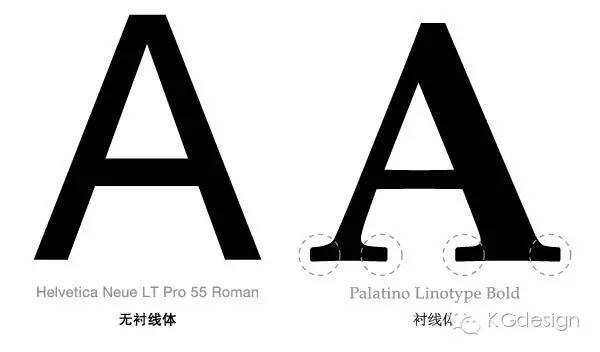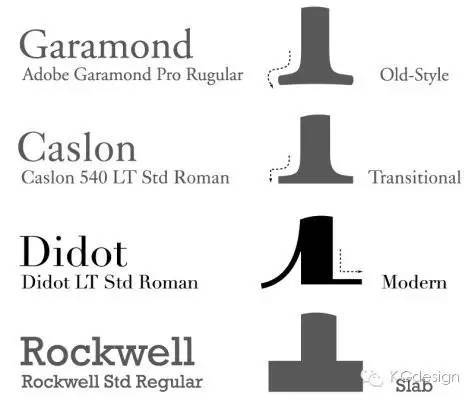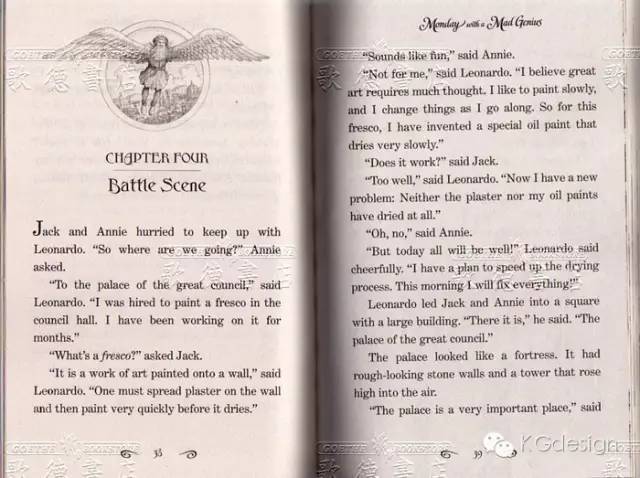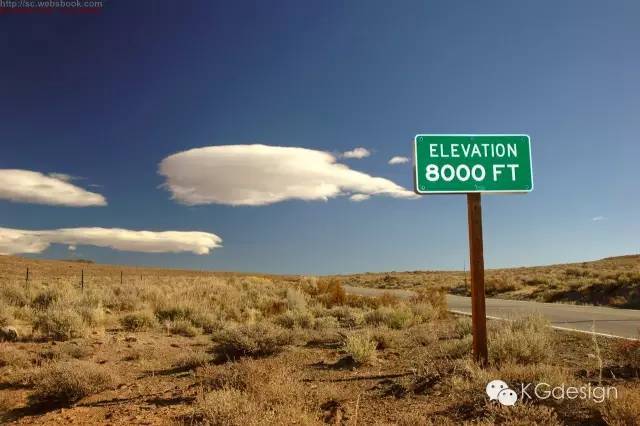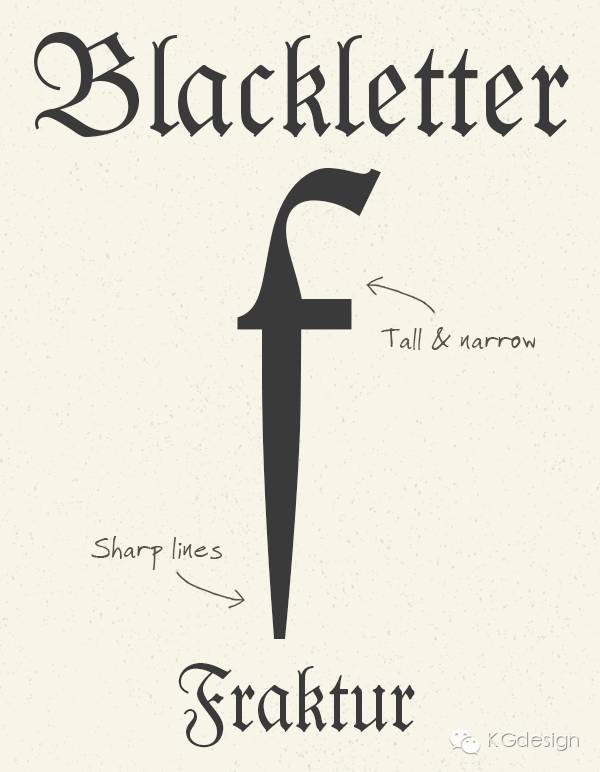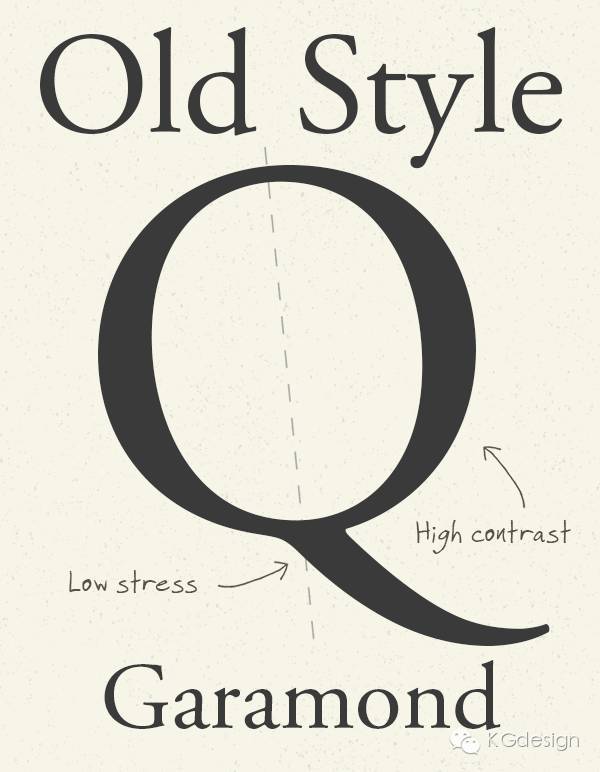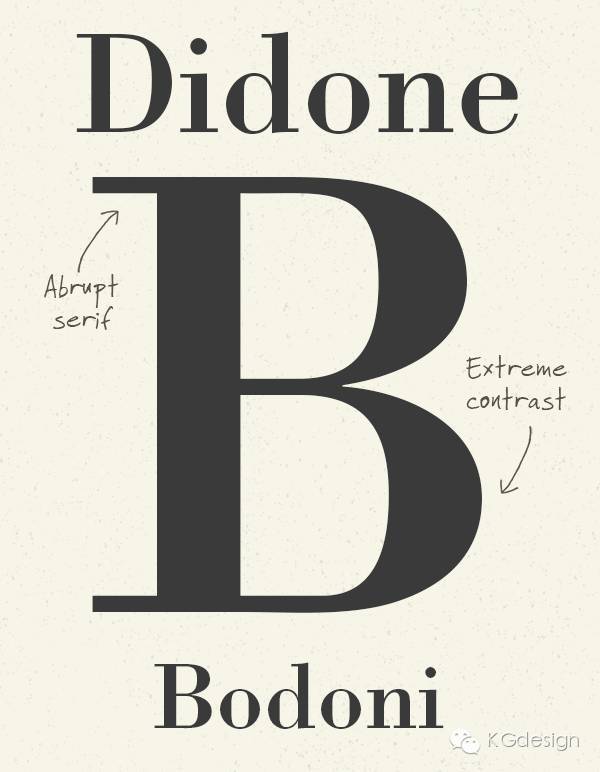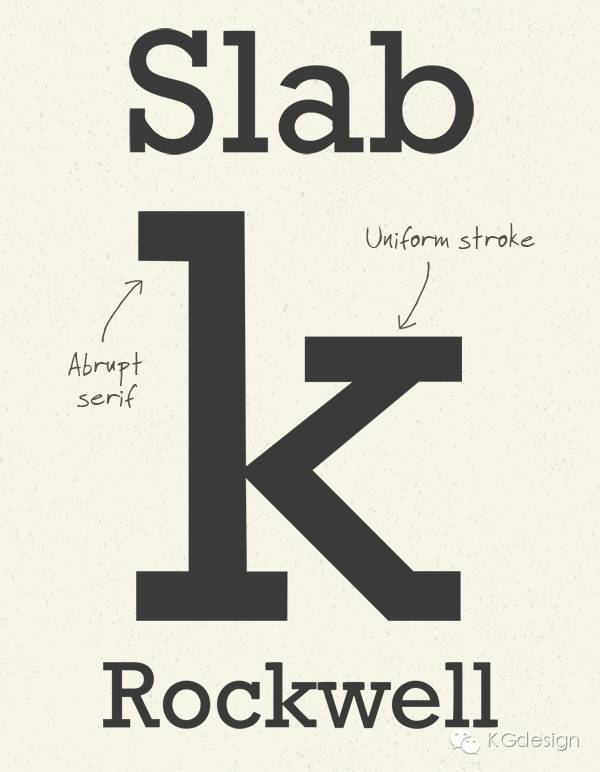
如何选择合适的字体?一文告诉你怎么办
在平面设计中,字体的重要性仅次于排版。不同于活字印刷的年代。以如今的网络环境而言,有成千上万种字体可以供设计师和各类从业者自由下载,那么当我要排一份ppt、论文、海报、画册时应该如何选择字体?这里试着简单的表达一些我对这个问题的理解。
将成千上万种字体进行归类和总结是个费神的工作,印刷工人和设计师们将字体粗分为衬线字体、无衬线字体、手写体三个类别。
手写体就不废话了,先来明确一下什么是所谓的衬线
如上图所标注的
衬线指的是字体笔画末端的装饰线条。
一般认为所谓的衬线最早是在操作雕版印刷时为了避免平行于木纹的线条破损,所以开发出的横向线条纤细而纵向线条粗壮的字体。
设计师总是倾向于在段落文字中使用衬线字体。因为衬线体被认为比无衬线体更易于阅读,是更正统而与正式的。
相对的各种标牌与指示系统则大量的使用无衬线字体,相信是出于易于辨别与制作成本的考虑。
衬线体
这种存在了几个世纪的字体在设计中主要用于表达专业、古老、正式、传承一类的情感。横竖线条的线宽差越大越会表达出强烈的女性风格。在实际使用中又被细分为哥特、旧式衬线、过渡衬线、新古典主义衬线、粗衬线等形式。
哥特体
风格太过于浓烈以至于很少有机会用到,极为夸张华丽,有意思的是在德国直到二战时期仍然有很多人将这个字体用于日常书写。也是古登堡的活字印刷机所使用的字体。
旧式衬线
旧式衬线体可以追溯到15世纪末的罗马字体(有意思的是现在依然有很多人用罗马体来指代衬线字体。)这种字体是基于文艺复兴时期教士手写字体的基础上得来的。特征在于强调对角线。字母粗细变化最明显的位置并不在x或y轴上,而是在一条倾斜的对角线上。旧衬线字体在设计时会遵循一个严格的斜度,用来统一整个字体的基调。
从名字上就能理解,旧式衬线在使用中会给人以强烈的历史感。如果你需要赋予一个设计沧桑或者经过时间洗礼的感觉,那么你应该在旧式衬线体中寻找你需要的字体。
过度衬线体
这种字体出现于18世纪中叶,印刷业的飞跃式发展使得商人们迫切需要一种更易于开发和使用的字体来优化生产效率。在这样的历史背景下由Baskeville创造了一种轴线垂直的衬线字体。因为这种字体结合了旧式衬线体的一些特征,却又融入了新古典主义的一些元素,所以被称为过度衬线体。著名的times new roman就是过度衬线体。
在历史感减弱的同时,女性特征变得更加明显,时尚感也得以加强。这也是各种时装品牌所青睐的字体。
新古典主义衬线体
随着媒体的发展与印刷技术的普及,印刷商们不再满足于仅仅是细节不同的各种印刷字体而是而是需要一款在第一时间就能吸引人们注意的完全不同的设计。于是20世纪中叶,这种专为标题而生的新式衬线体被开发了出来,它基于古典风格,却有着夸张的纵向线宽,同时将衬线做得细长。这种字体夸张的形态在那个年代极好的完成了吸引眼球的工作。通常用于各种时尚产品宣传的引文和标题。
粗衬线体
十分粗暴而显眼的风格,在19世纪被大量使用在通缉令和海报广告中的字体,特征是与文字线宽相等的衬线,这种大胆的设计来带的是极为抓眼的效果和糟糕的段落文字特性,是一种只能用于标题的字体。
无衬线体
简单的来说就是没有衬线的字体,可以对应黑体以方便理解。无衬线体因为在印刷史上出现的时间较晚,整体风格也更干净整洁,所以更适合新潮、科技、整洁的情感表达。大类上分为歌德体、几何体、人文体几种。
歌德体
歌德体是最基本、最流行、也是最常用的无衬线字体,这种字体开发的初衷是希望开发出一种更简单、易于识别、几何化的字体用于印刷流程。但是在开发之初却并不被人们所承认。看惯了无衬线体的受众把这种字体称为怪诞体。然而出色的识别性和易于制作的特征却仍然使得这种字体流行了起来。
总的来说所有歌德体都是在视觉感受上中性偏男性的字体形象。理性而果断的线条适合新闻机构使用。较细的线宽在小屏幕上显示时也有更清晰的优势。
新歌德体
泛指1900年以后的歌德体,也是目前所谓的标准无衬线字体。大名鼎鼎的Helvetica和Arial都是这个系列的一员。与歌德体相比字形更加圆润饱满,视觉感受也稍微现代一些。但区别并不大,使用场景也并无太大的不同。
几何体
这是一种基于几何形状,尽量只使用原型和正方形拼接而成的字体。由于在较细的线宽下圆形会占据远大于直线条的空间,是无衬线字体中少有的可能获得偏女性视觉印象的无衬线体。
总的来说几何体适合表达科技感与刻板、冷静、规矩的情感。在现代感的表达上拥有天然的优势。
人文体
这种字体来源于古罗马的碑铭。这种最具书法特色的无衬线体拥有强烈的笔画粗细变化,配以笔画末梢的装饰。有着无衬线字体中最优秀的可读性。适合需要衬线体与无衬线体风格结合的地方。也是所有无衬线字体中最适合段落文本的选项。
文字作为信息传播的主要载体之一,一直拥有不同的情感属性,根据内容与表达形式确定适合的字体是任何需要进行信息传达的人都应该认真学习的基本功,也是提升内容品质不可或缺的一环。